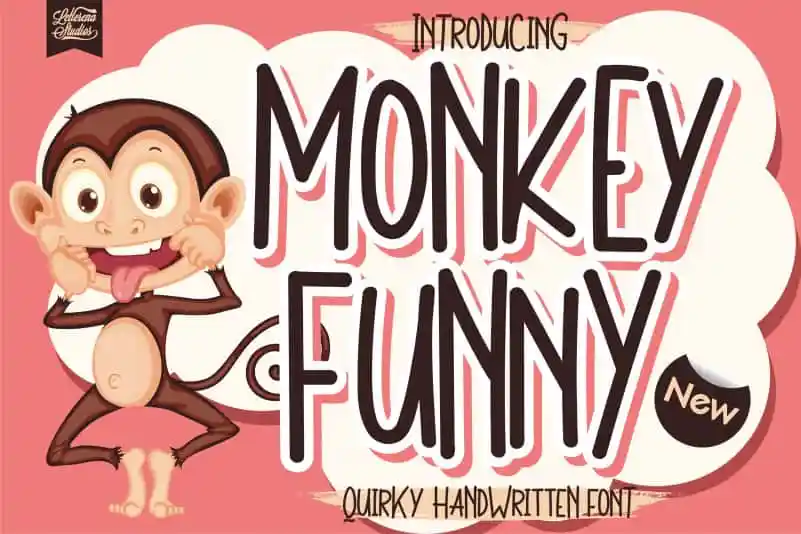
A fonte “Monkey Funny Display Font” é uma seleção simples e natural que reflete a escrita manuscrita. Com traços finos e altos, esta fonte é perfeita para um grande range de aplicações de design, tanto formal quanto informal. É perfeitamente adaptada para criar um visual divertido e único em sua próxima criação grafica. Ideal para designers que buscam uma fonte única e descompromissada, a “Monkey Funny Display Font” é certamente um excelente adquirir para seu banco de fontes favorito.